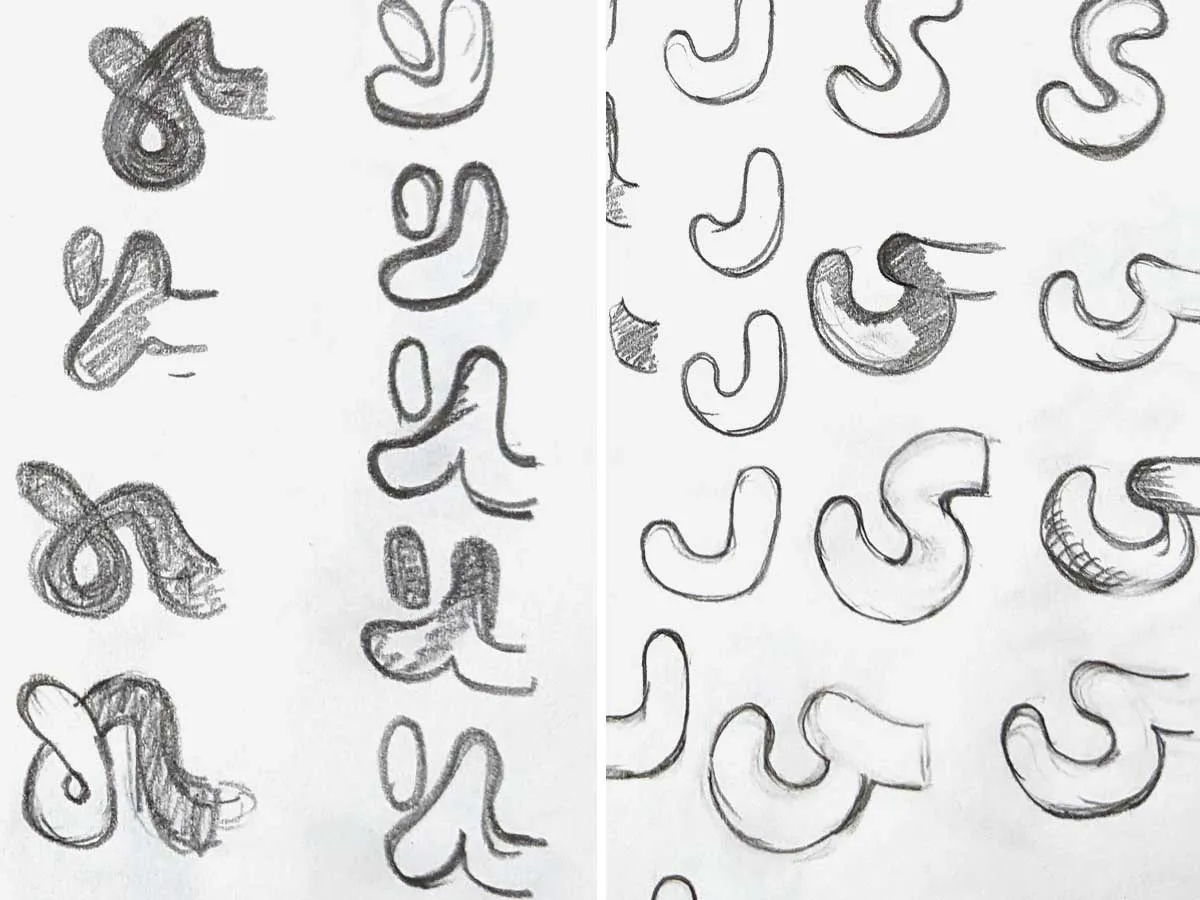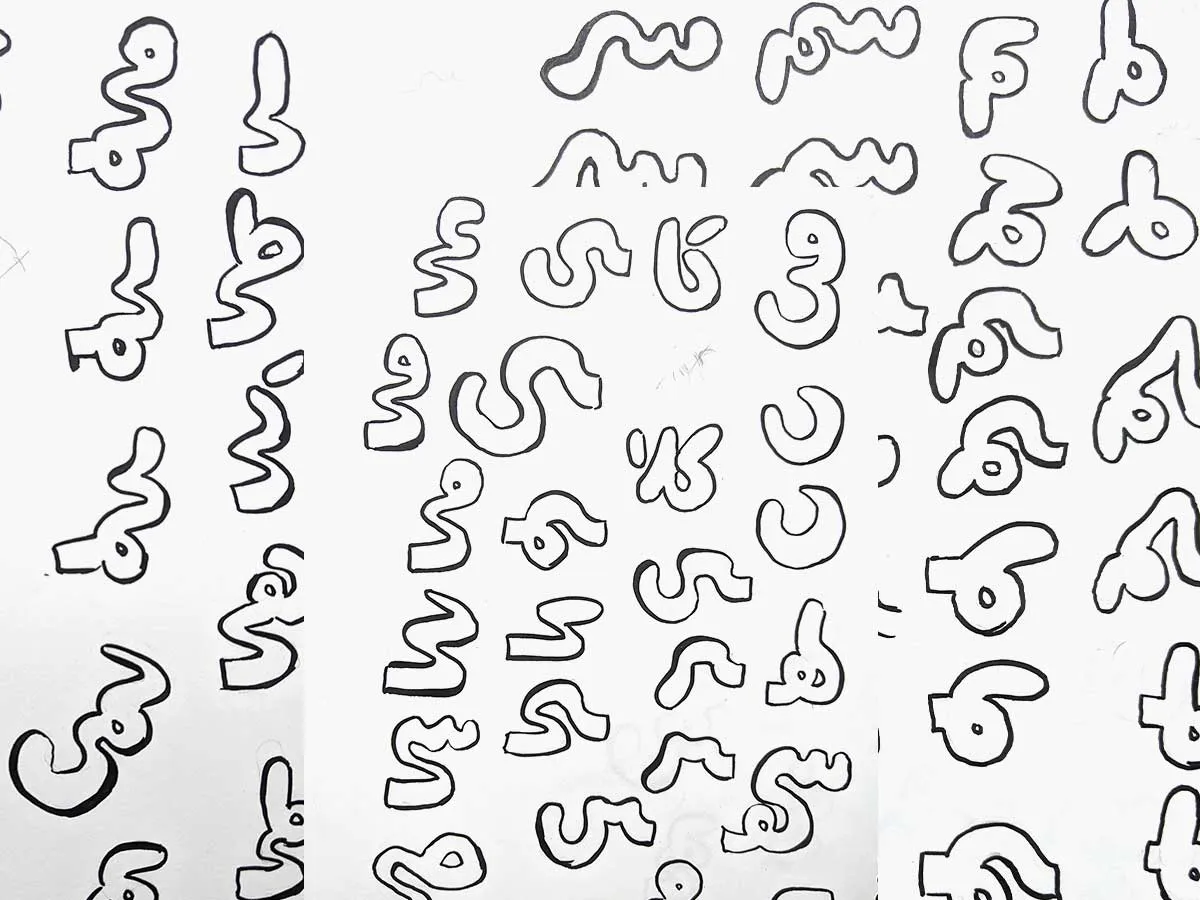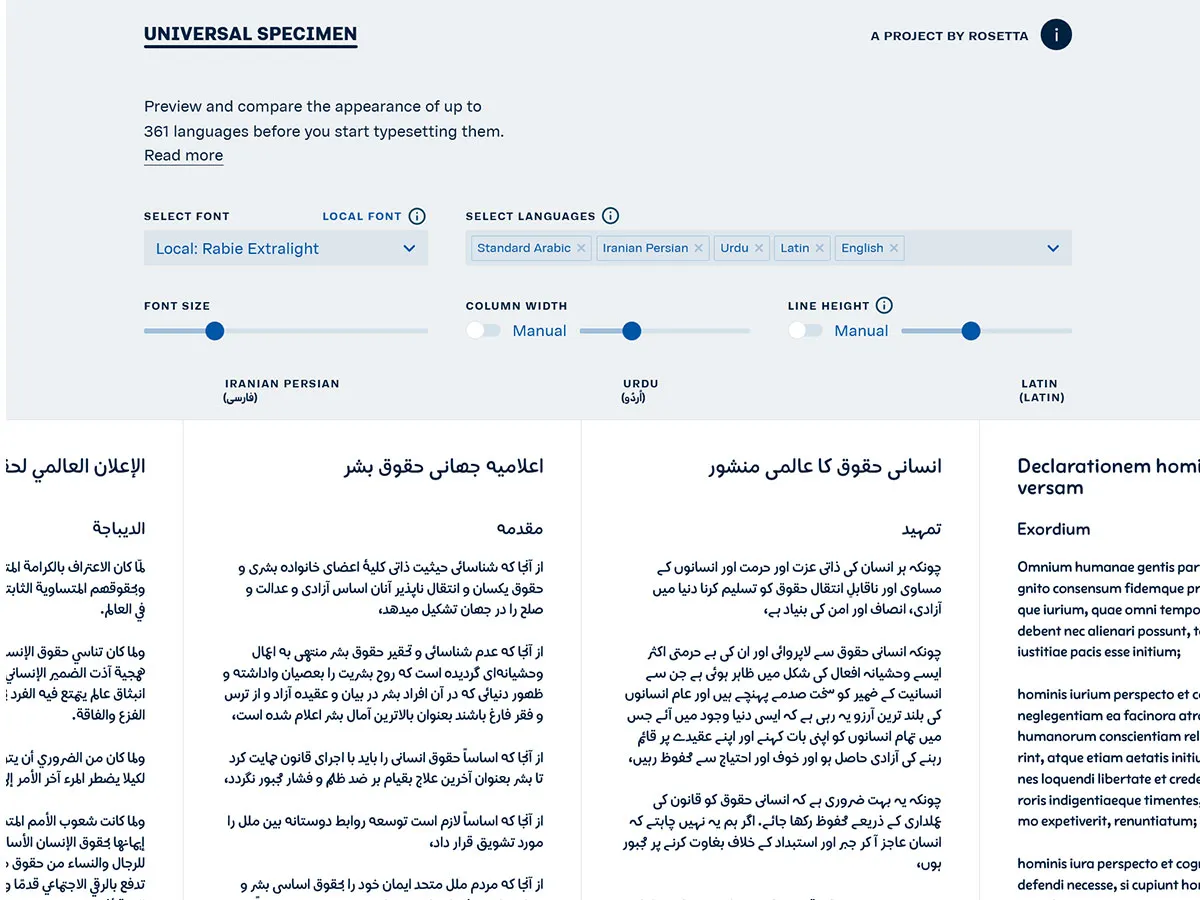
أنجذب إلى قدرة الخطوط اليدويّة على جعل التصاميم شخصيّة وفريدة. الخطوط اليدويّة التي عملت عليها حتى الآن - كخط طبشور ونسمة - خطوط مكتوبة يدويًّا، لذا تحمست لتجربة نوع جديد، ألا وهو الخطوط المرسومة يدويًا.
لتوضيخ الفرق، فإني أعني بالخطوط المكتوبة: الخطوط التي تحاكي كتابة الشخص نصًّا بيده باستخدام أداة كتابة كقلم أو طبشور. أما الخطوط المرسومة يدويًا فإني أفسرها بأنها رسم لشكل/إطار الحرف يدويًّا ثم تحويله إلى خط رقمي.
مررت بفترة في العام الماضي أُعجَب فيها بالخطوط مبالغة السماكة، وقررت أن أرسم خطًّا عربيًا، سميكًا ولطيفًا في نفس الوقت، لأخوض تجربة جديدة.
رسمت أولًا شكل الحروف في أسمك حالاتها. أتذكر نصيحة تقول أن البدء بتصميم أسمك وزن في الخط يسهل رسم بقية الأوزان لاحقًا؛ نظرًا إلى أن تكبير المساحات البيضاء في الأوزان الرفيعة بعد ضبطها في السميكة - أسهل من تصغيرها في السميكة بعد أن تُضبط في الرفيعة. تخيل أنك رسمت شكل حرف «مـ» رفيعًا أولًا. إذا سمّكت الحرف لاحقًا من الداخل، عليك مراعاة ألّا تطمس المساحة البيضاء داخل الحرف، أو تصغّرها إلى حد يؤثر على مقروئية الخط. أي أنّك قد تضطر إلى المرور بتعديلات أكثر إذا بدأت بالوزن الرفيع عند تصميم خط يدوي.
رسوم خط ربيع الأولية للوزن السميك
لجعل الخط أكثر عفوية، وأقل «رقمية» رسمتُ أشكالًا مختلفة لأجسام الحروف المتشابهة (مثل ج ح خ). أردت أيضًا إضافة العديد من الأشكال للحرف الواحد: مثلًا ثلاثة أشكال لحرف الجيم المفرد، حيث أنه عندما يكتب المستخدم حرف «ج» بهذا الخط يحصل على واحد من الأشكال الثلاثة عشوائيًّا. إضافة خاصية العشوائية ممكنة تقنيًا ببرمجة الخط لاحقًا لتغيير شكل الحرف حسب الأحرف المجاورة له، أو ترتيبه مقارنة بمحيطه وهكذا. على أي حال، اخترت عدم إضافة هذه الخاصية لمراعاة الحفاظ على وزن معقول لملف الخط؛ فكان لا يزال لدي كمّ من الأحرف المقرونة بانتظار إضافتها!
بالحديث عن الأحرف المقرونة، هي عبارة عن دمج لحرفين أو أكثر في محرف واحد. أي أنها أشكال خاصة تنتج عند طباعة أحرف بترتيب معين. رسمتُ العديد من احتمالات الحروف المقرونة الثنائية (دمج حرفين) والثلاثية (دمج ثلاثة أحرف) لاعتبار إضافتها في الخط. اتضح لاحقًا أن الحروف المقرونة من أجمل مميزات خط ربيع.
الرسوم الأولية للحروف المقرونة في خط ربيع
تختلف طريقة تحويل الرسوم اليدوية الأولية إلى رسوم رقمية «فيكتور» باختلاف الشكل المُراد لإطار الحرف «آوت لاين». أحيانًا أستخدم التحويل التلقائي في برنامج يدعم الفيكتور (مثل برنامج إلستريتور) عندما أريد الإبقاء على الخامة/الشكل اليدوي والعفوي. أما حين أهدف إلى الحصول على حدود ناعمة ومثالية للحرف، فإنني أعتبر الرسوم الأولية مرجعًا فقط أرسم عليه إطار الحروف مجددًا كمنحنيات بيزيه في برنامج صناعة الخطوط.
هذه المرة أدخلت جميع صور الرسوم الأولية إلى برنامج إلستريتور وحولتها إلى فيكتور بأداة «Image trace». اخترت أفضل أشكال الحروف من المجموعة، ثم نقلتها حرفًا حرفًا إلى برنامج فونت كريتور (FontCreator).
من عيوب تحويل الرسوم الأولية إلى فيكتور تلقائيًّا بأداة كـ «Image trace» أنها تولّد في إطار الحرف نقطًا غير ضرورية. لذلك بعد نقل كل حرف إلى الخانة الخاصة به في برنامج الخطوط، ضبطت المنحنيات حيث أني قللت عدد النقاط في كل حرف مع الإبقاء على النقاط الأساسية في أقصى أطراف إطار الحرف قدر الإمكان.
رقمنة حرف الهمزة وضبط الرسم والمنحنيات
بإضافة خصائص «أوبن تايب» (OpenType features) يتحول الخط من مجرد أشكال حروف منفصلة - كما هو الحال في النص الإنجليزي - إلى حروف متصلة ببعضها صالحة للكتابة بالعربية. أحتاج في هذه المرحلة من تصميم الخط إلى تكوين كلمات وجمل بالخط لمعاينته أثناء تعديله، ومقارنة شكل الحرف بالحروف المحيطة به، للتأكد من أنه يناسب الشكل العام للخط؛ فالخط نظام يجمع حروفًا متناسقة فَضْلاً عن كونه تجميعًا لحروف جميلة فرديًّا. لذلك أضفت خصائص أوبن تايب الأساسية إلى الخط، مثل مواقع الحروف (ابتدائية، وسطية، نهائية) وتركيب ومواضع علامات التشكيل والمحارف المقرونة، ثم بعد ذلك واصلت تعديل أشكال الحروف.
سأخوض في تفاصيل أكثر عن خصائص أوبن تايب في مقالة قادمة بإذن الله.
إضافة خصائص أوبن تايب
بعد أن عدلت أشكال الحروف إلى درجة لا بأس بها، أضفت إلى الخط ما تبقى من خصائص أوبن تايب؛ ضبطتُ المباعدة في النصين العربي واللاتيني، وأضفت بدائل سياقية في النص اللاتيني لتغير شكل بعض الحروف إذا كُتبت متتالية مثلًا.
بدائل سياقية - Alternates
المباعدة - Kerning
حروف مقرونة - Ligatures
وهكذا أنهيت تصميم أول وزن في الخط، مكونًا من 838 حرف، وانتقلت إلى تصميم بقية الأوزان.
نسخت حروف الوزن السميك إلى طبقة جديدة داخل برنامج الخطوط لاستخلاص الوزن الرفيع منه. استخدمت أولًا أداة تغيير الأوزان تلقائيًّا لأحصل على الوزن الرفيع، ولكن لأن الأداة تقارن أشكال المنحنيات رياضيًّا قد تنتج أشكال منحنيات غريبة وغير جميلة. لذا لم أكتفِ باستخدام تلك الأداة، بل واصلت تعديل الوزن الرفيع بمقارنة شكله مع السميك وتحريك النقاط يدويّا في إطار كل الحروف حتى وصلت إلى شكل الخط الرفيع النهائي.
العلاقة بين الوزنين السميك والرفيع في حرف الدال
يتبع تغير شكل الحروف تغيرات في خصائص أوبن تايب أيضًا. مثلًا إذا كانت الحروف في الوزن الرفيع أقصر منها في السميك، يجب ضبط مواضع علامات التشكيل مجددًّا، للحفاظ على مسافة مناسبة بينها وبين الحروف. قيم المباعدة بين الأحرف قد تختلف أيضًا في الوزنين لأن المساحات البيضاء مختلفة فيهما، وهكذا.
ضبط مواضع علامات التشكيل في الوزنين السميك والرفيع
إذا رسمت وزنين في برنامج الخطوط، يستطيع البرنامج توليد تدرجات أوزان وسيطة بين الوزنين يحددها المصمم. المهم أن تتساوى عدد النقاط ومواضعها في إطار الحروف في الوزنين كي ينتج البرنامج الأوزان الوسيطة بصورة صحيحة. أنتجت خمسة أوزان وسيطة بين الوزنين السميك والرفيع.
الوزنان السميك والرفيع، وخمسة أوزان وسيطة بينهما
صورة من نماذج عرض خط ربيع
أعلاه تلخيص لسبعة أشهر قضيتها في تصميم خط ربيع، وتوثيق لتجربة تحويل خط مرسوم يدويًا إلى خط رقمي.
رقمنة الخطوط اليدويّة تفتح المجال لإمكانيات لا حصر لها. كانت عملية رقمنة خط ربيع تجربة جديدة في حد ذاتها، وسعيدةٌ أني خرجت منها بنتيجة مُرضية. شاهد العرض الكامل لخط ربيع النهائي.